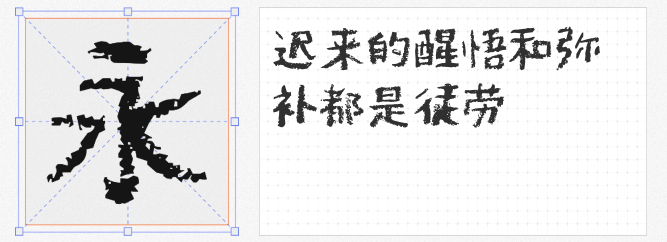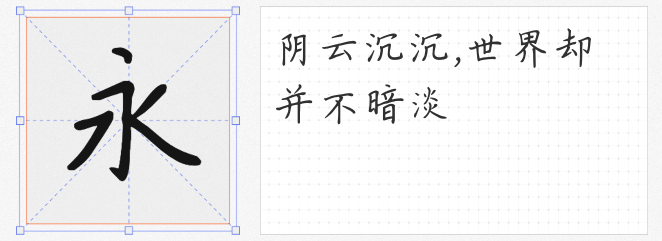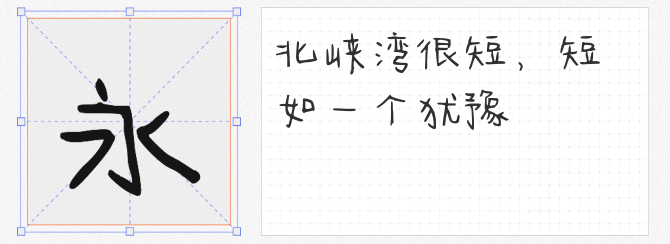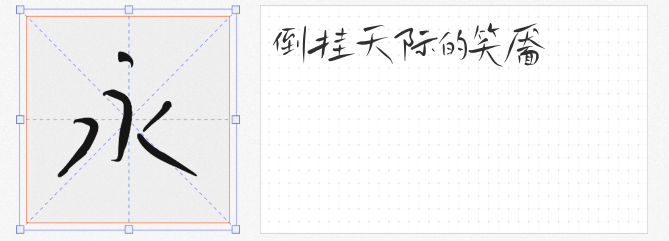
在追求效率与规范化的数字时代,手写字体以其独特的温度感和人文气息,成为设计师打破机械感、传递情感的首选。本文精选四款免费商用手写字体,从随性洒脱到童趣治愈,满足不同场景的创意需求。
由作者亲自手写的「鸿雷拙书简体」,以自然流淌的笔触展现无拘无束的创作状态。字型结构松散却不失平衡,笔画粗细变化自由,仿佛能看见书写者运笔时的呼吸节奏。这款字体适合用于文化海报、艺术展览标题或文艺类书籍封面,传递返璞归真的意境。其「拙」中见巧的特质,尤其适合需要弱化商业感、强化人文情怀的设计场景。
「PF频凡胡涂体」以油漆或蜡笔在粗糙表面涂抹的质感为灵感,墨迹斑驳厚重却暗藏温柔。笔画边缘的颗粒感与不规则留白,赋予文字岁月沉淀的文艺气质。推荐用于动漫标题、诗歌短文排版或手账类设计,其「未完成感」能瞬间拉近与受众的距离。尤其适合需要营造复古氛围或强调手工温度的场景,如独立杂志、文创周边等。
由张清平先生逐字书写的「瑞美加张清平硬笔楷书」,完整覆盖GB2312标准字符集,兼具实用性与艺术性。字体以硬笔楷书为根基,笔画刚劲有力却不失温润,结构严谨中透出书卷气。作为免费商用字体中的「正统派」,它适用于学术论文排版、传统文化类海报或需要权威感的品牌标识,为设计注入专业性与文化底蕴。
「今年也要加油鸭」以短促的笔画出头和略显笨拙的构字骨架,塑造出天真烂漫的视觉效果。字型自带「未成熟感」,如同孩童初学写字时的稚嫩笔迹,特别适合少儿教育、萌宠用品、美食包装等需要传递治愈感的领域。在社交媒体中作为个性化用字,也能瞬间提升内容的亲和力与传播力。
这四款字体各具特色,共同构建了手写字体的多元表达。设计师可根据项目调性自由组合,让文字成为传递情感与个性的视觉载体。所有字体均支持免费商用,为创意工作提供更多可能性。